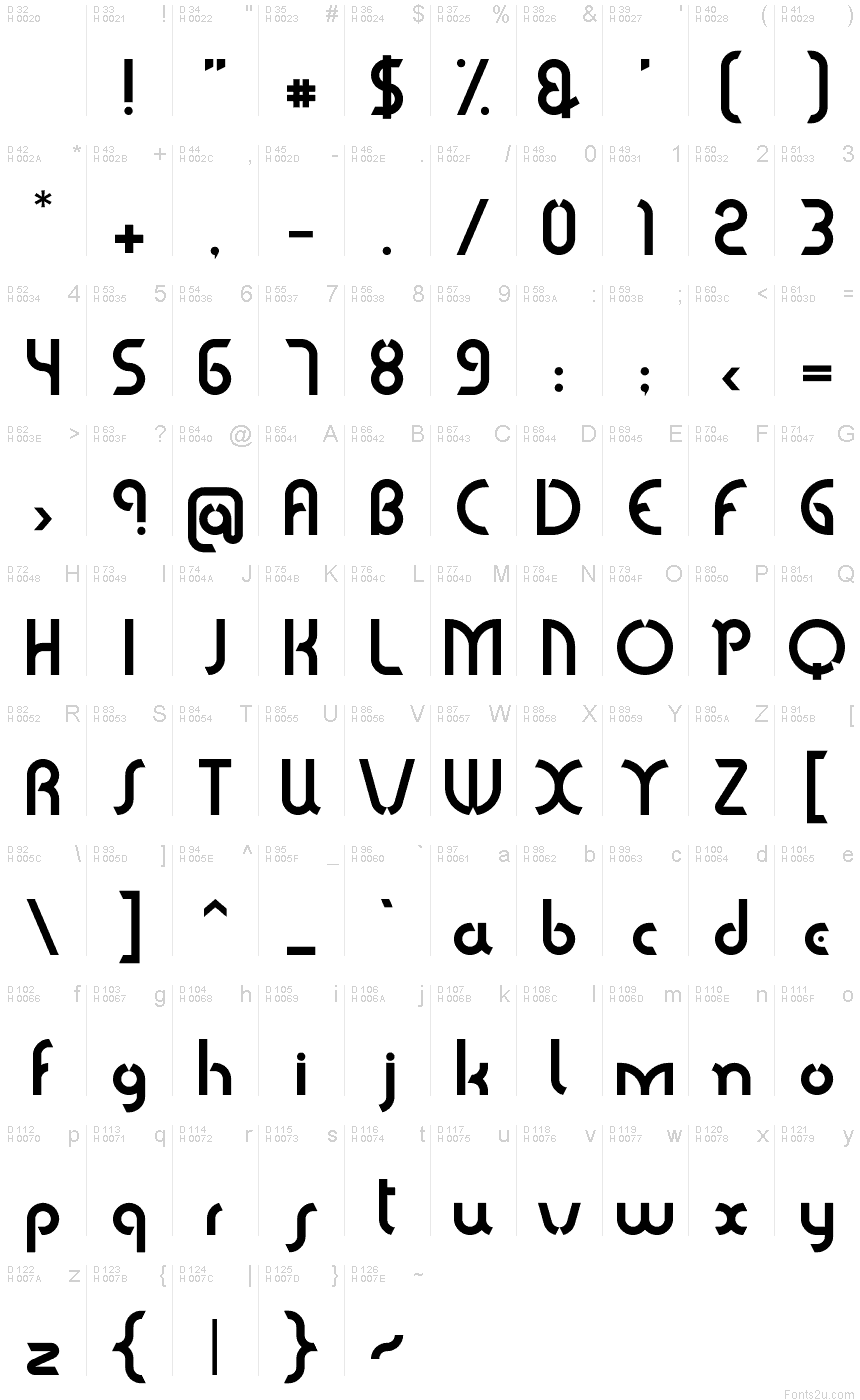
Sabomaster to darmowy, retro font typu display, utrzymany w klimacie pop lat 70. Litery bazują na szerokich, zaokrąglonych formach i płynnych krzywiznach, a drobne, klinowate wycięcia w kształtach takich jak „a” czy „o” nadają alfabetowi zabawny, niemalże logo-typograficzny rytm.
Świetnie sprawdza się w grafikach albumowych, brandingu kawiarni, nagłówkach plakatów, opakowaniach i krótkich tekstach, gdzie ta miękka, ale wyrazista sylwetka może zbudować odpowiedni nastrój. Jako darmowy font, Sabomaster jest również doskonałym wyborem do plansz tytułowych, naklejek i logotypów, zwłaszcza gdy zależy Ci na tym, by kilka liter sprawiało wrażenie zaprojektowanych na zamówienie, nie przytłaczając przy tym nadmiarem zdobień.